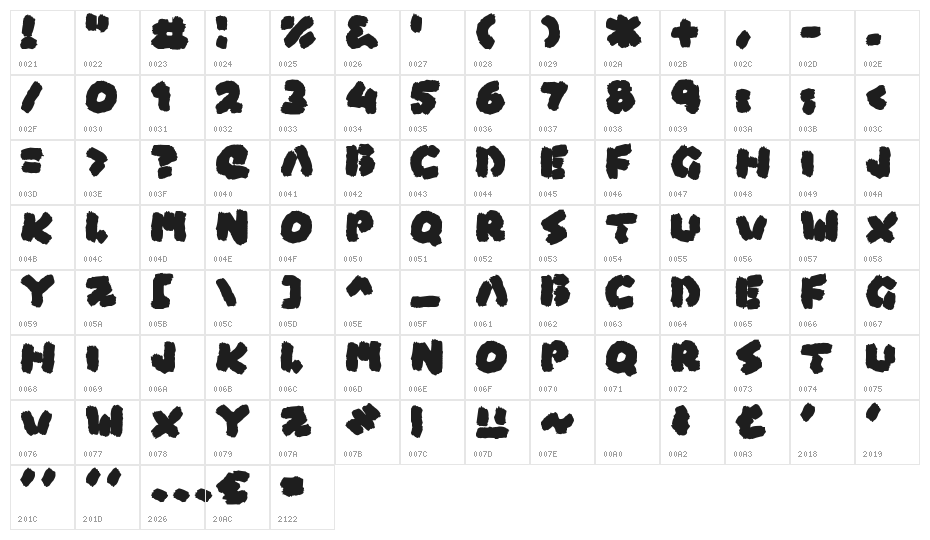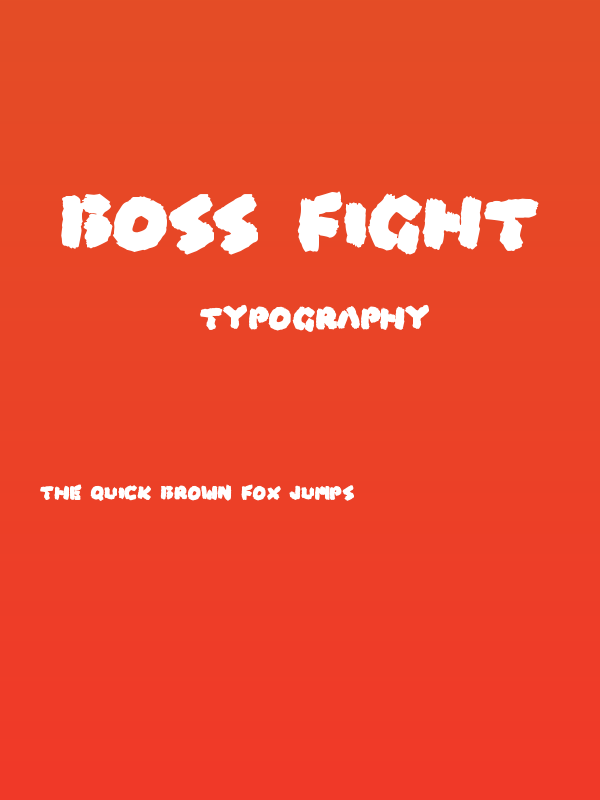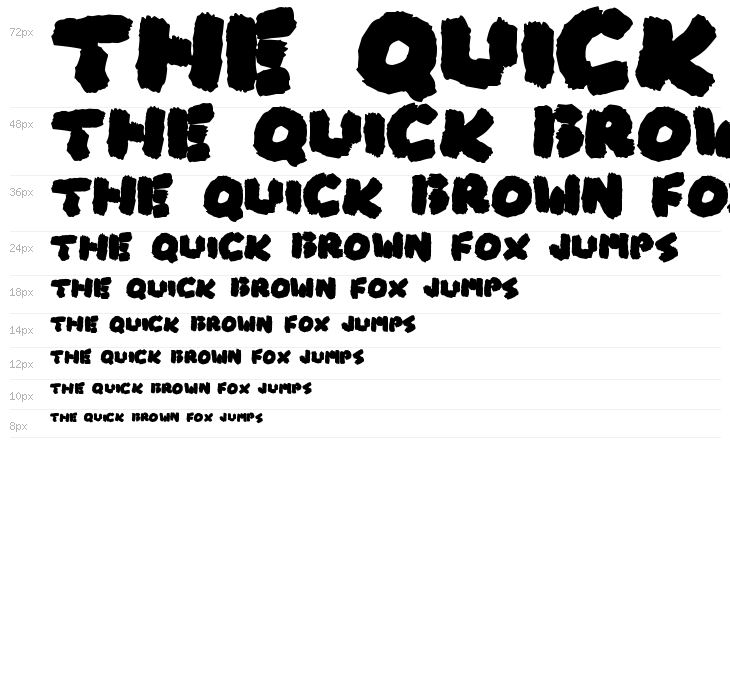
Boss Fight Font
| Gesamtstil | Modern, Artistic |
| Vorgeschlagene Projekte | Ideal for posters, album covers, streetwear branding, and any project needing a bold, artistic touch. |